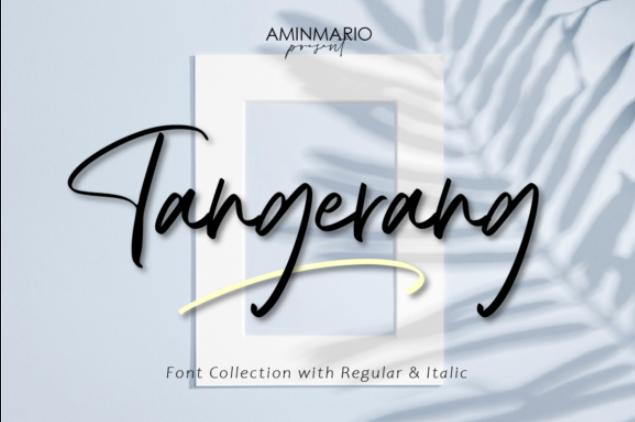
[Creativefabrica] Tangerang Font (aminmario)
Tangerang - это современный рукописный шрифт, читабельный, жирный и стильный. Он отличается плавными изгибами и идеально подходит для модного брендинга или редакционных дизайнов. Этот шрифт закодирован в кодировке PUA.